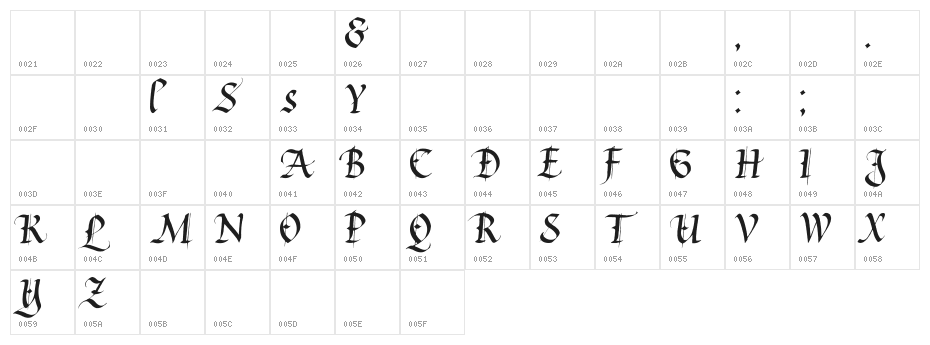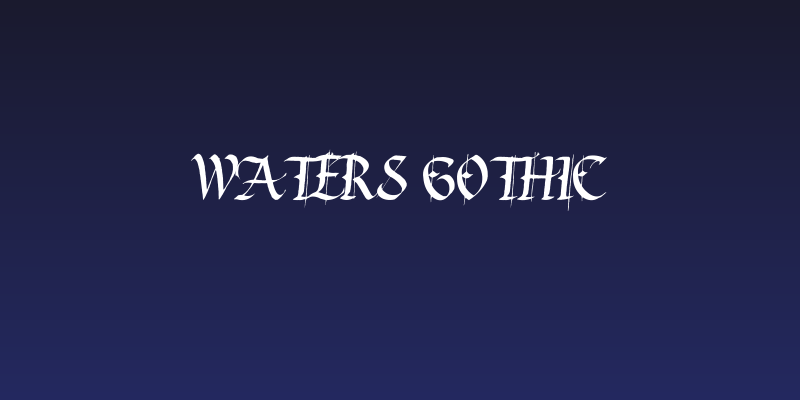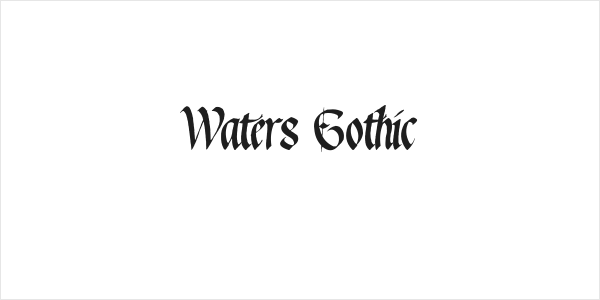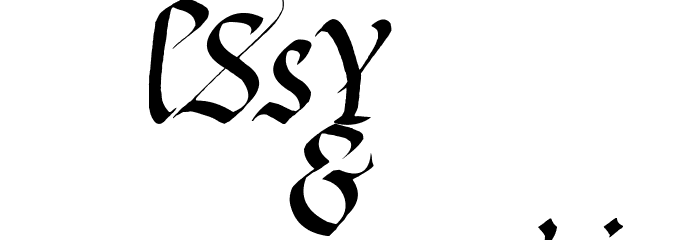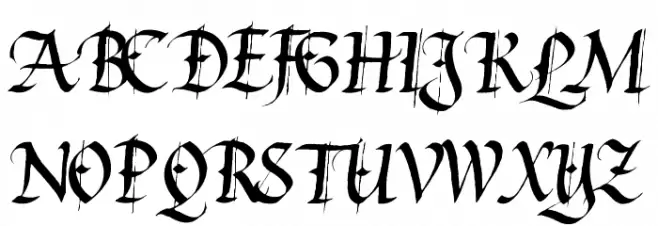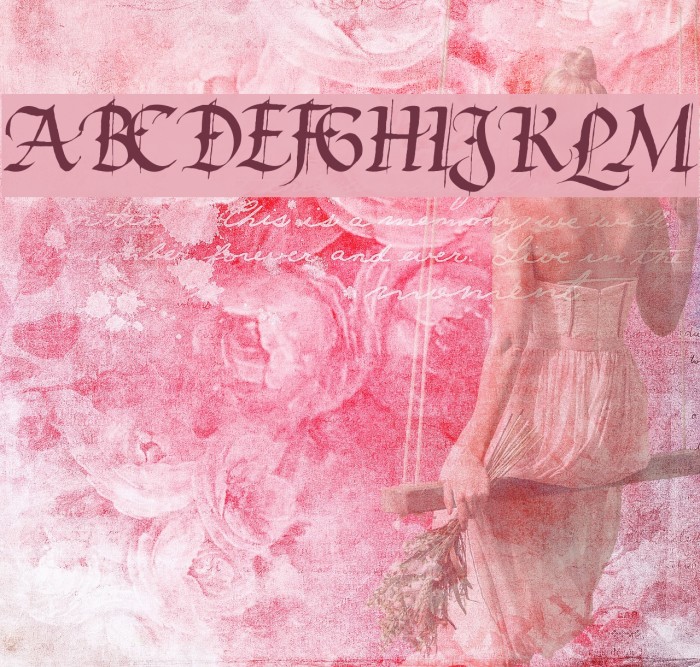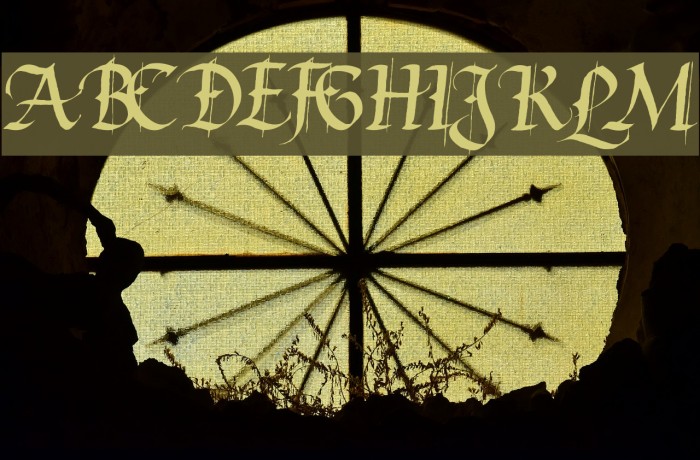
Waters Gothic Font
✎ Gothic
| Name | Waters Gothic |
| Kategorien | Gothic |
| Gesamtstil | Gothic, Decorative |
| Anwendungsfall | Logos, Headlines, Decorative text |
| Vorgeschlagene Projekte | Ideal for historical-themed designs, gothic posters, book covers, and decorative invitations. |